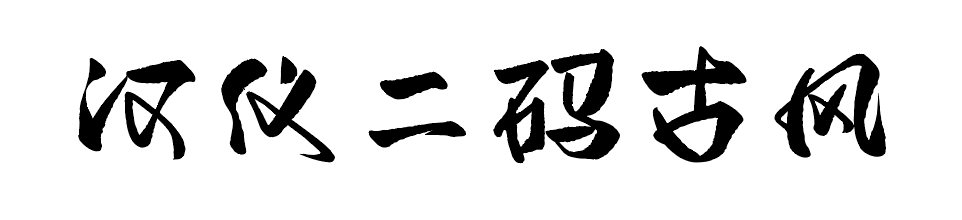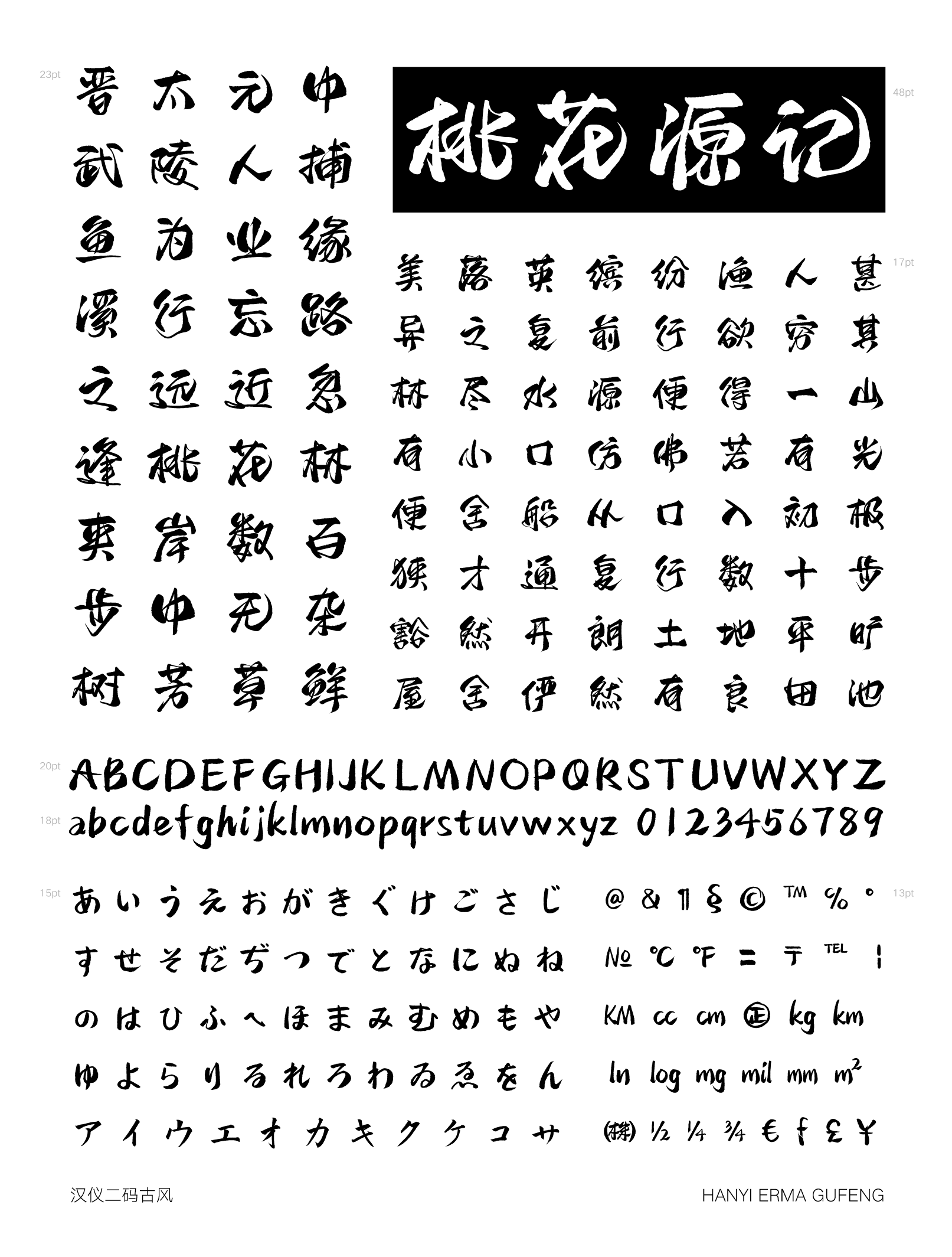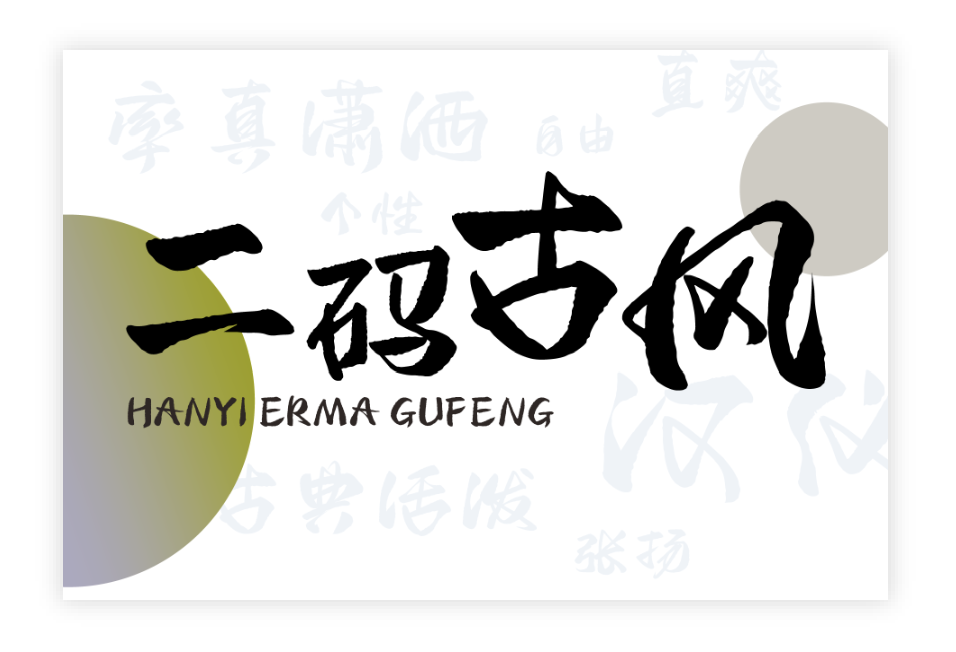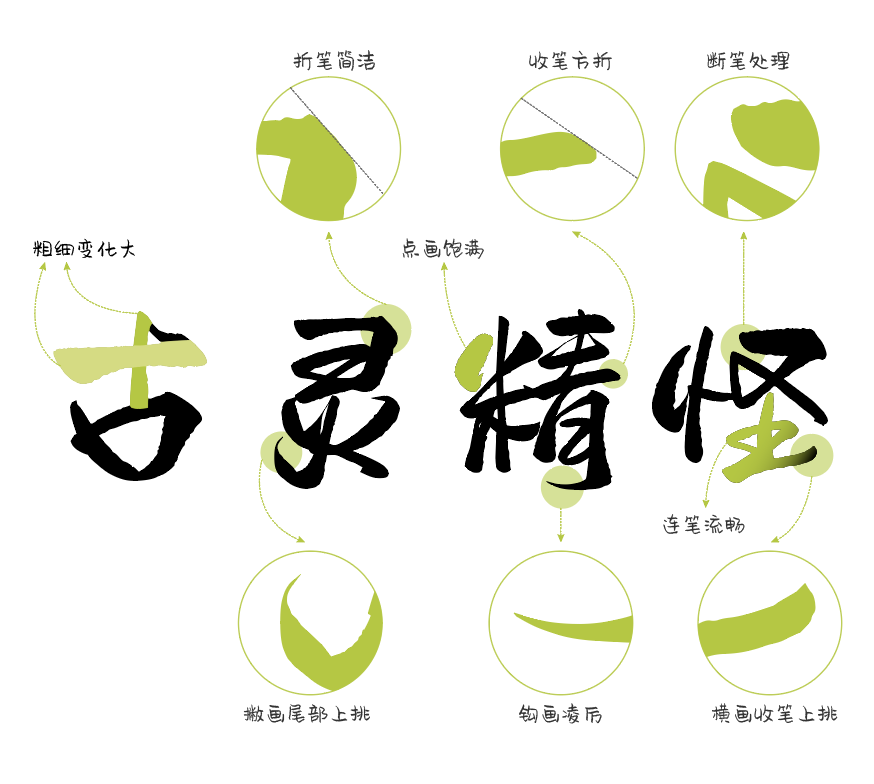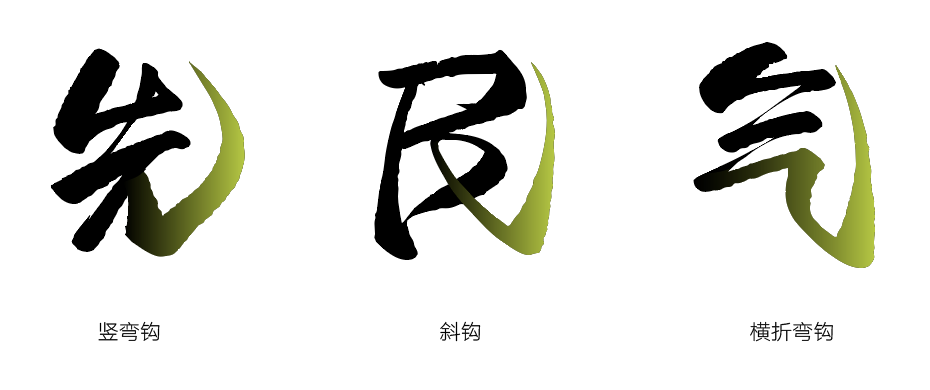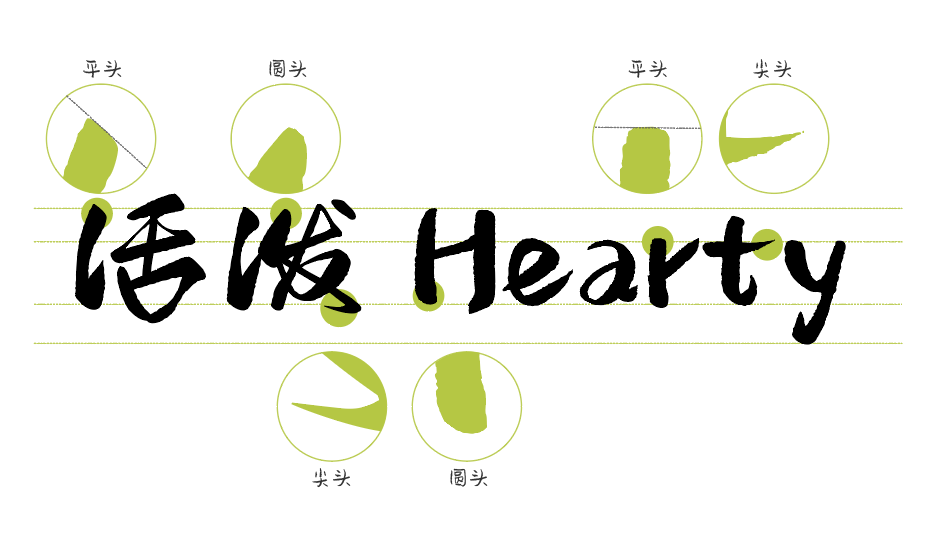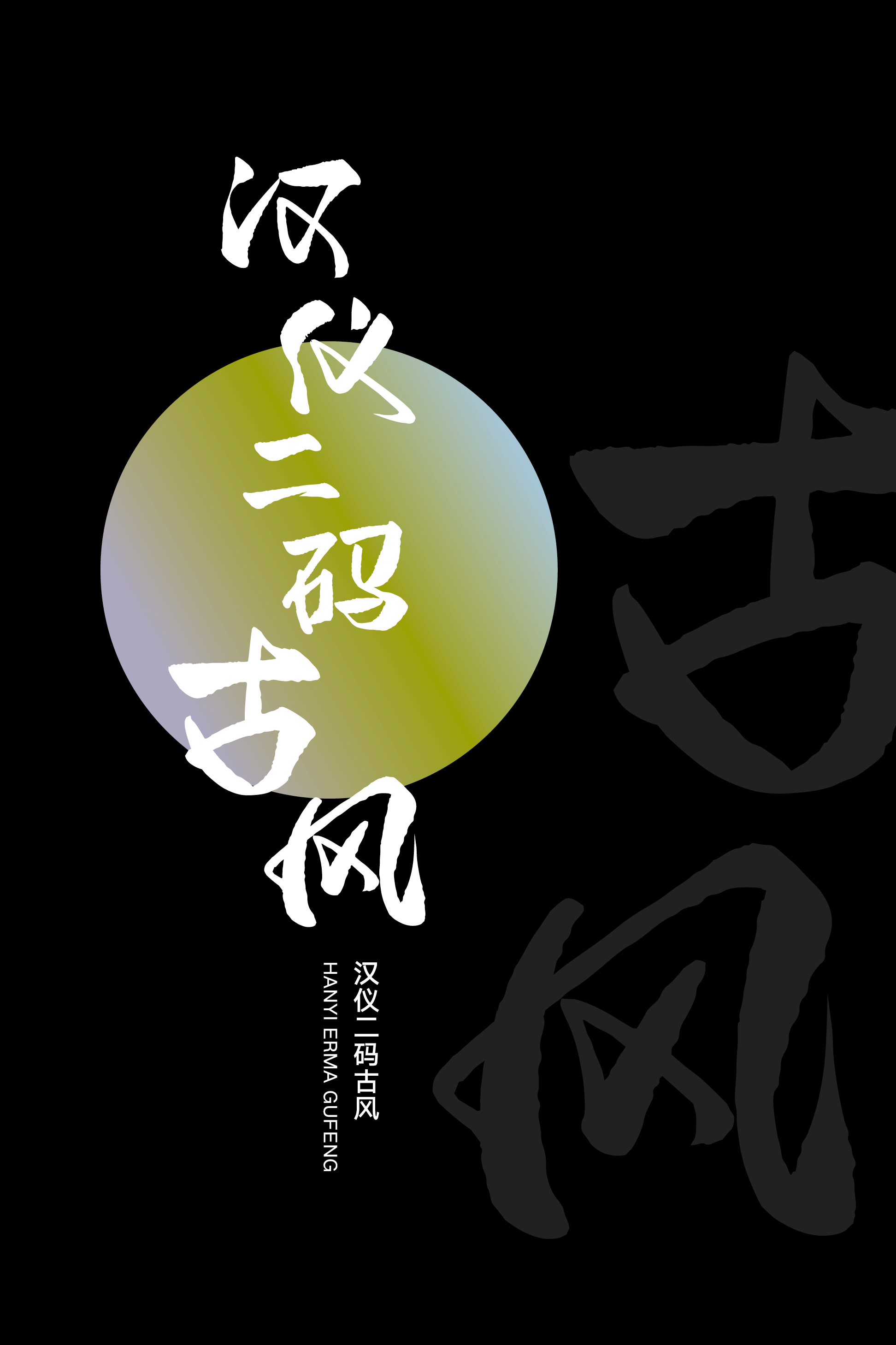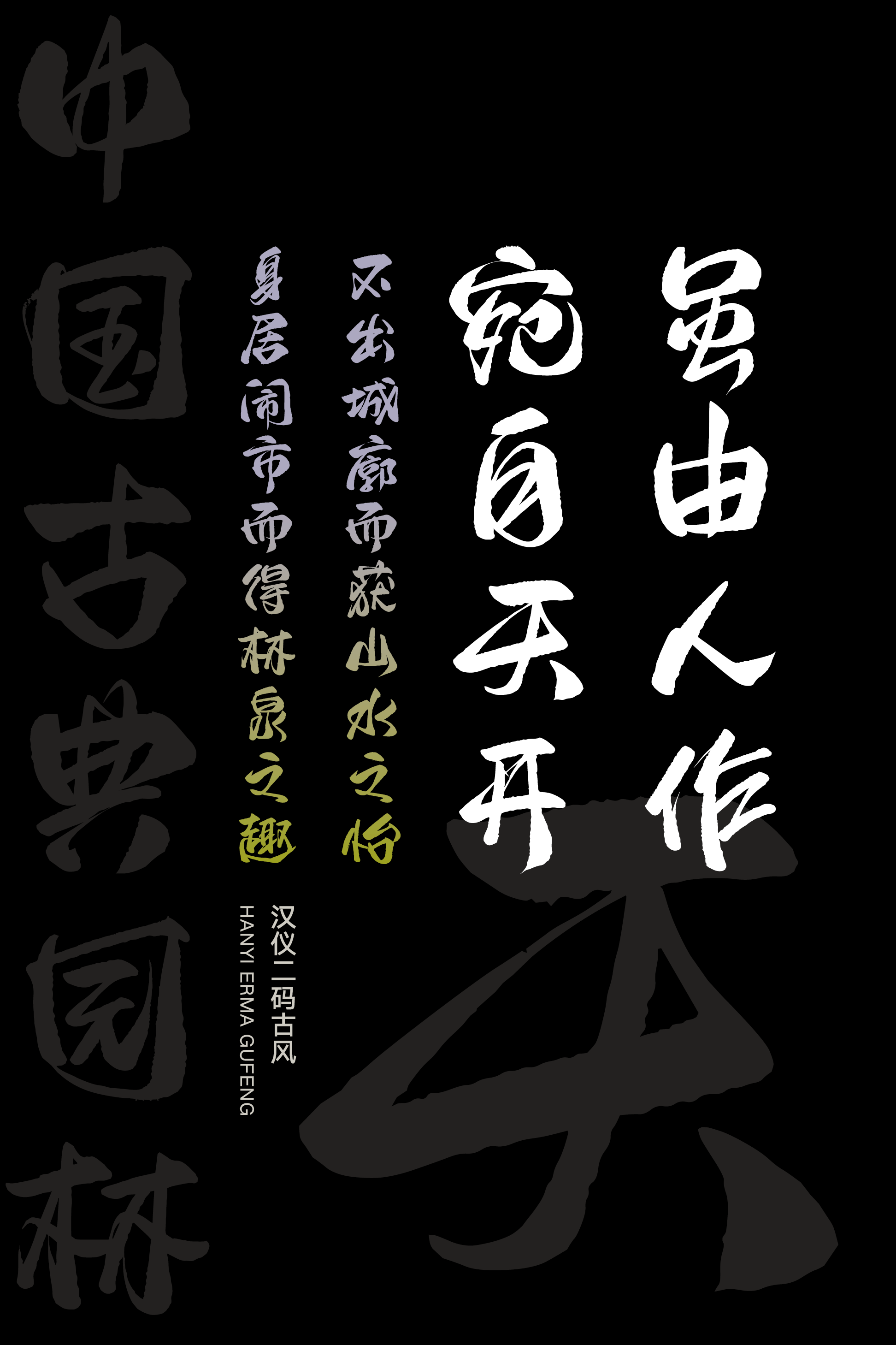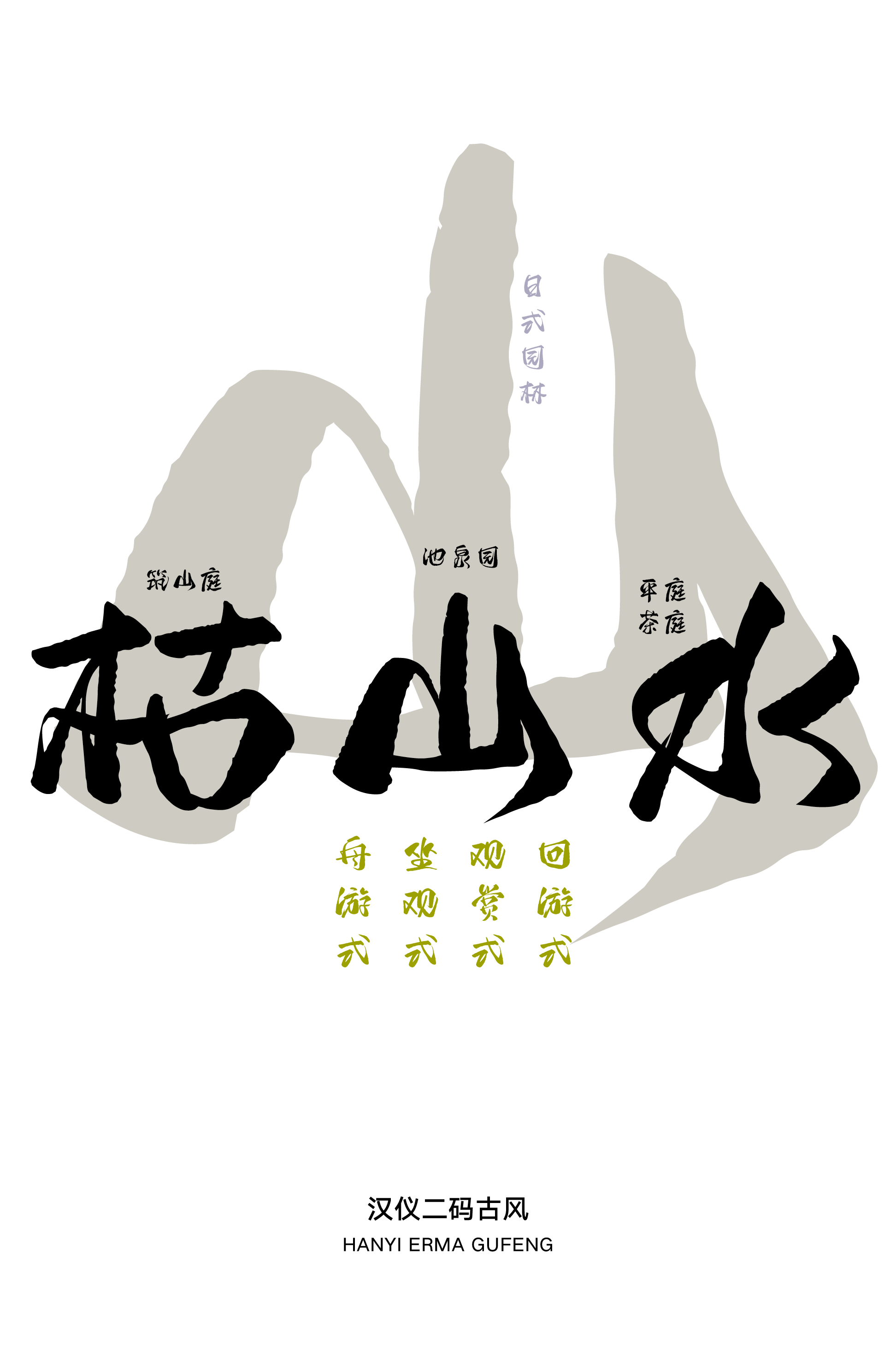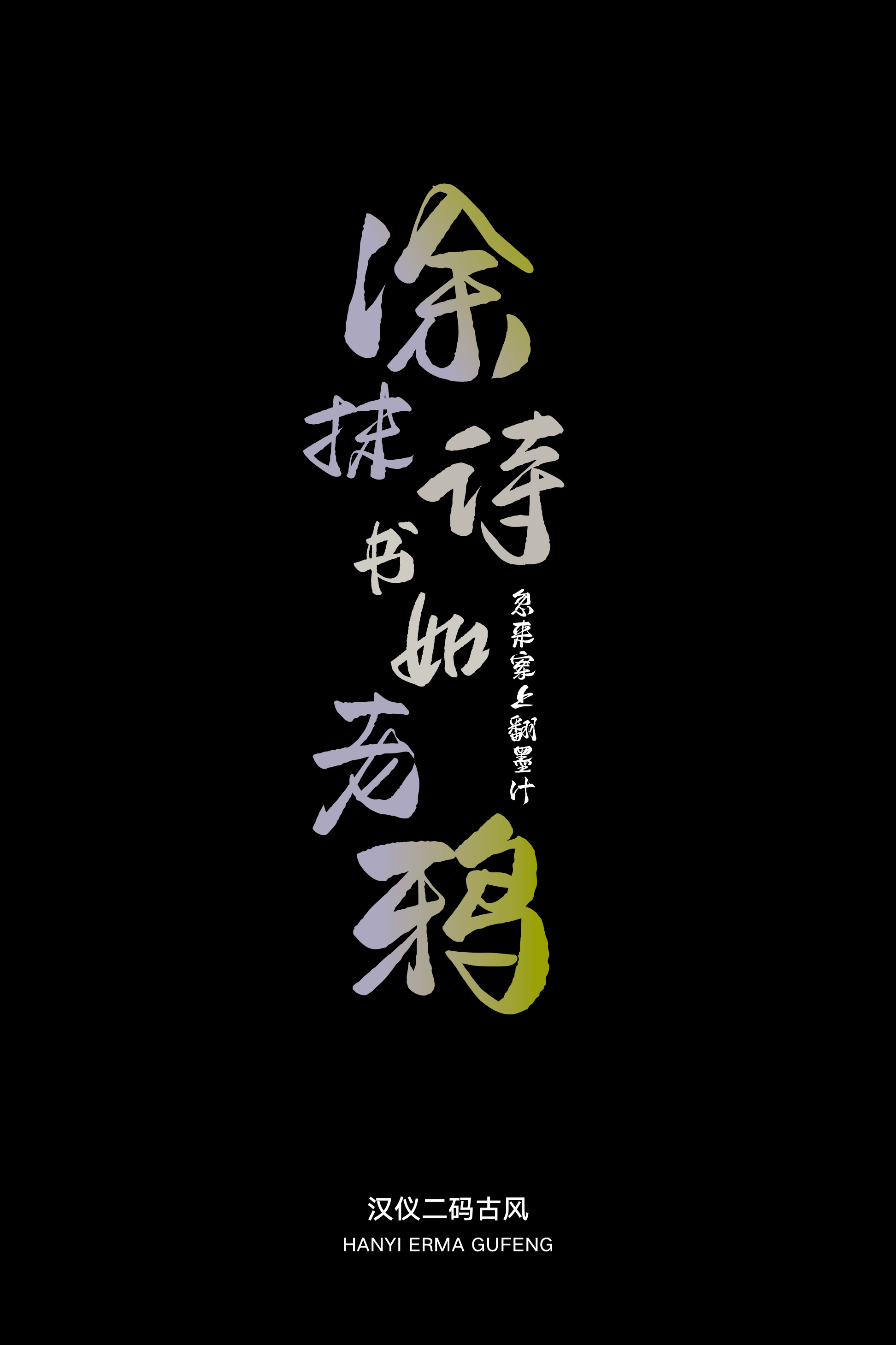
汉仪二码古风字体介绍,汉仪二码古风字体设计灵感
手书
中国风 / 率真 / 张扬 / 可爱 / 轻松 / 活泼
标志 / 广告 / 游戏 / 动漫 / 影视 / 包装 / 杂志 / 海报
汉仪二码古风|率性张扬
汉仪二码古风出自汉仪字库签约设计师泥二码,她擅长“手绘板书写”,是一位爽朗大方的东北姑娘。这是汉仪字库与二码合作开发的第二款字体,是一款率性潇洒,同时饱含力量的创意书写字体。
汉仪二码古风|结构特征
与二码墨书相比,汉仪二码古风的中宫收紧,笔画空间更加紧凑。
汉仪二码古风|笔画特点
汉仪二码古风在笔形处理上流露出一种张扬、直爽的个性特征, 作者用笔自由洒脱,连绵笔画中透出一丝行书笔意,使字体显得张力十足。
汉仪二码古风用连笔的方式加快了书写节奏,使字体书写更加灵活,有种一气呵成、快意江湖的感觉。
汉仪二码古风的钩画向上挑起,长长的一笔势展力足、十分豪放、肆意张扬。
汉仪二码古风|中西文匹配
汉仪二码古风的西文也是由作者泥二码书写完成,保持了和中文一致的性格特征——率性洒脱、肆意张扬。
汉仪二码古风|排版展示
汉仪二码古风|字体海报